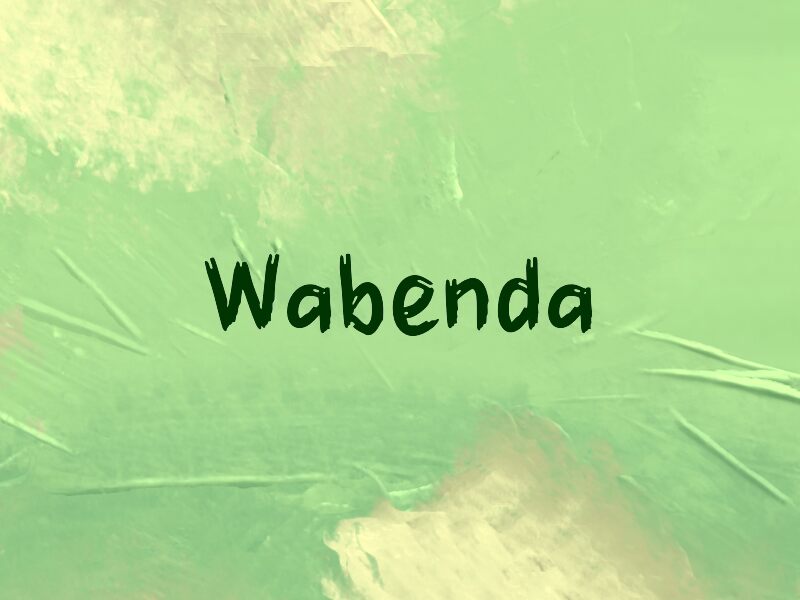
Wabenda
Wabenda от Wep — это бесплатный «грубый» кистевой шрифт с непринужденным, рукописным ощущением. Буквы словно набросаны на бумагу наспех: рваные края, неровные соединения и тупые окончания штрихов сохраняют текстуру «живой» и необработанной.
Он отлично подходит для музыкального оформления, заголовков на плакатах, обложек зинов, стритвир-графики и ярких баннеров для соцсетей, где нужен бесплатный шрифт, который выглядит броско и немного небрежно. Благодаря широкому и простому ритму кисти, Wabenda лучше всего смотрится в коротких строках, заставках и крупных надписях, позволяя своей дерзкой, живописной динамике говорить за себя.